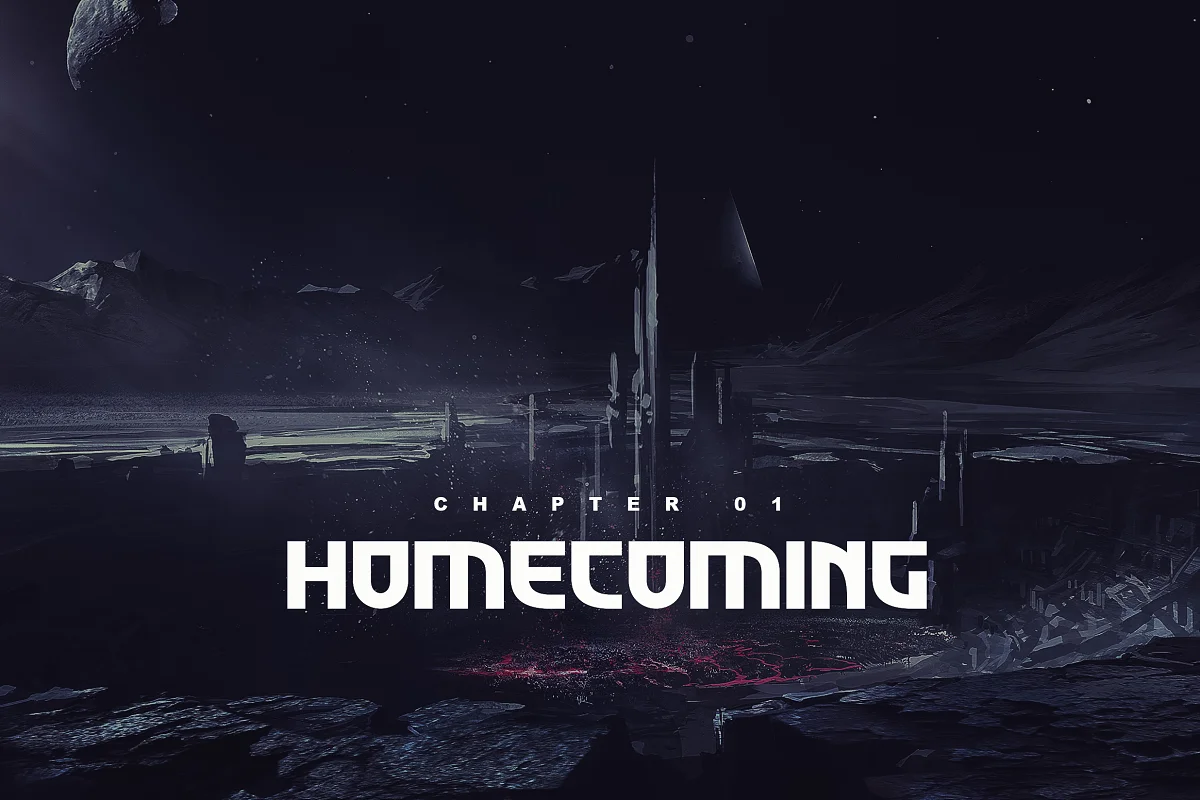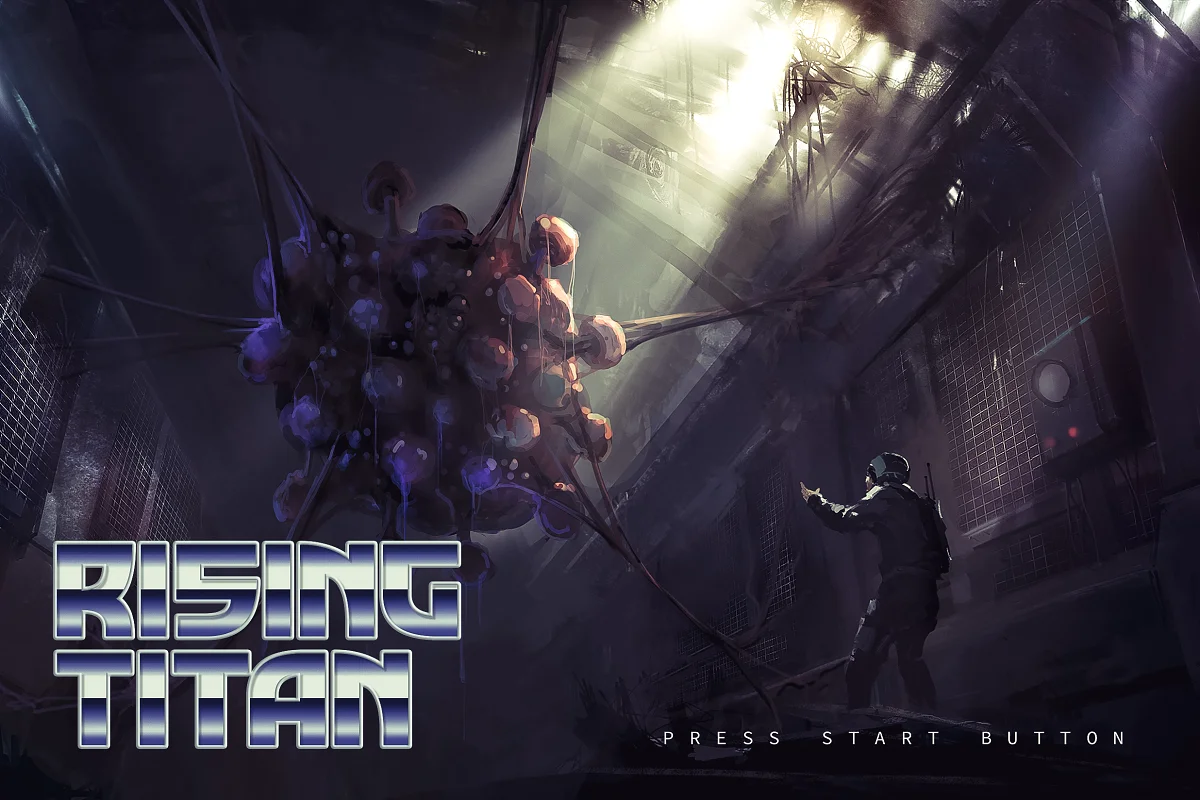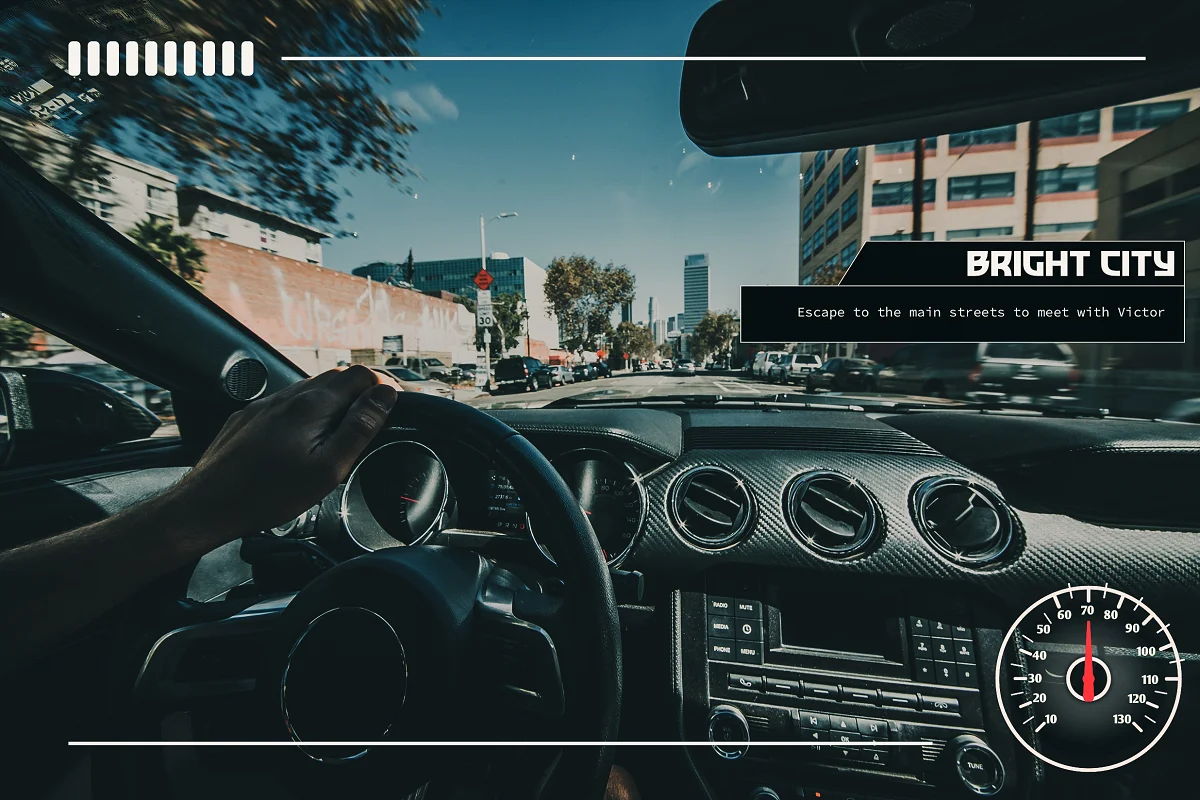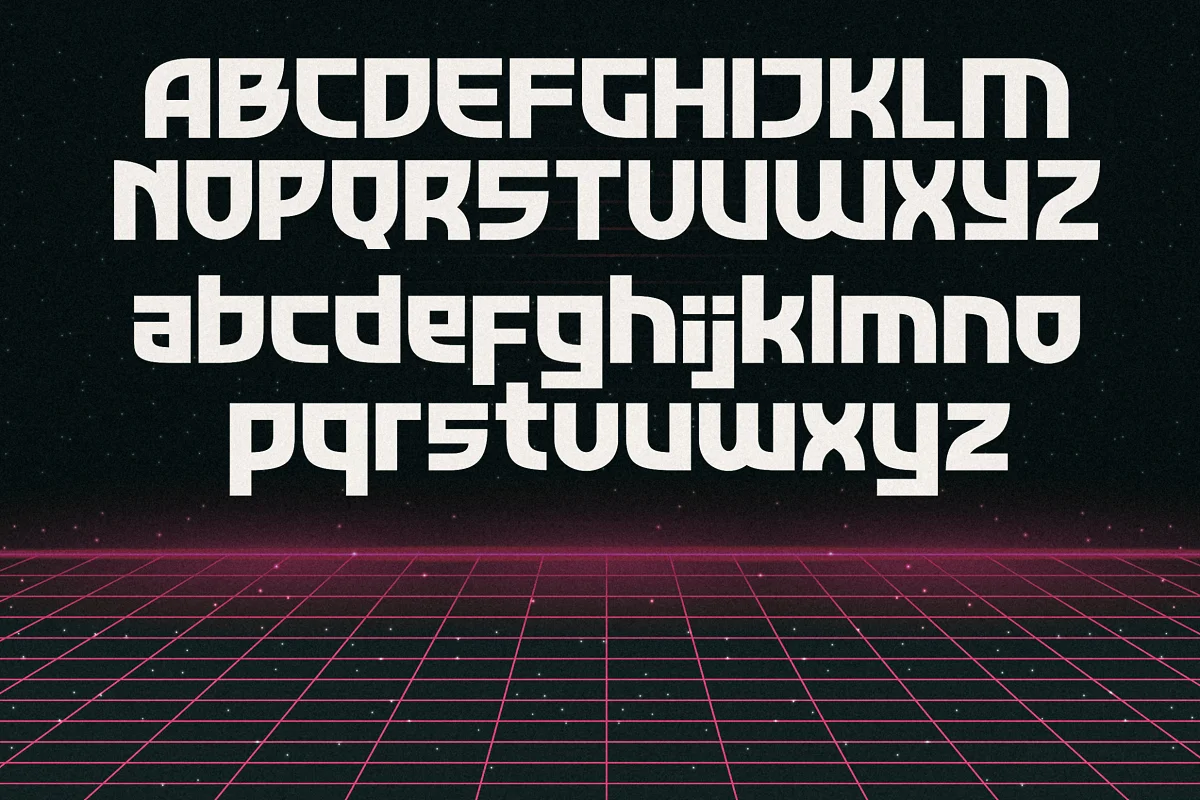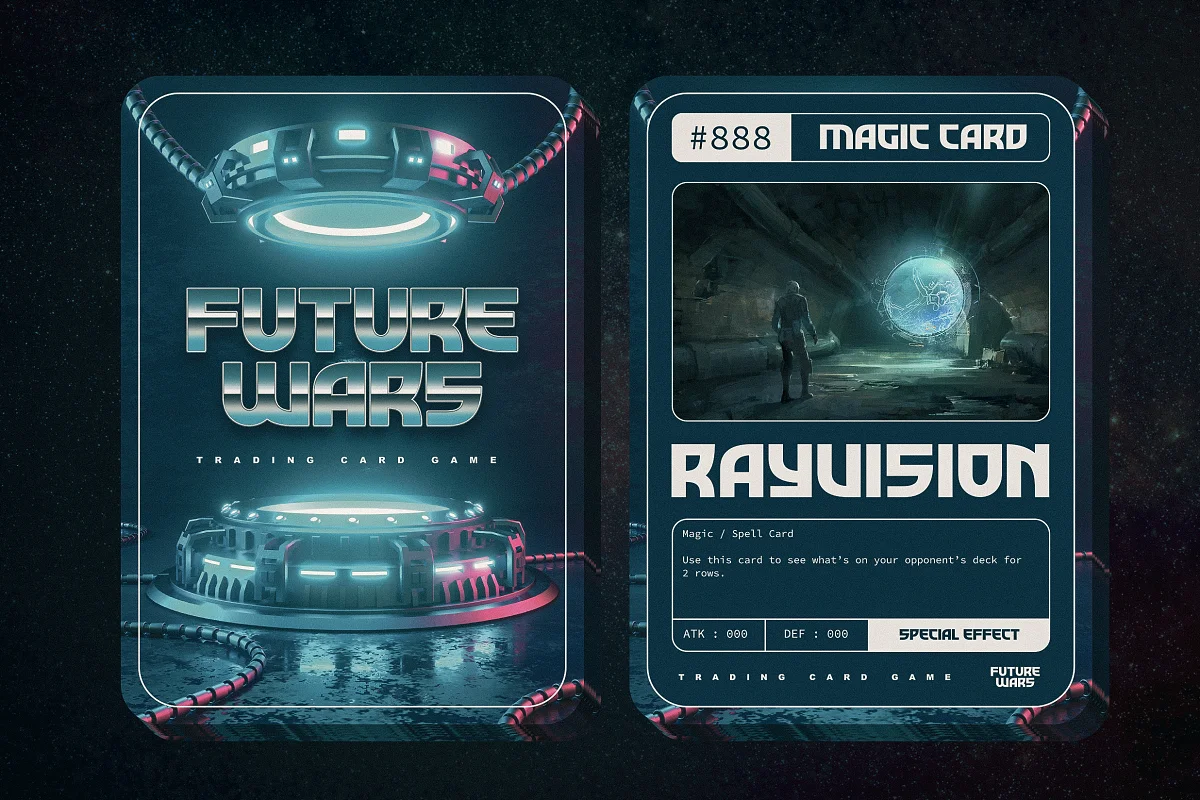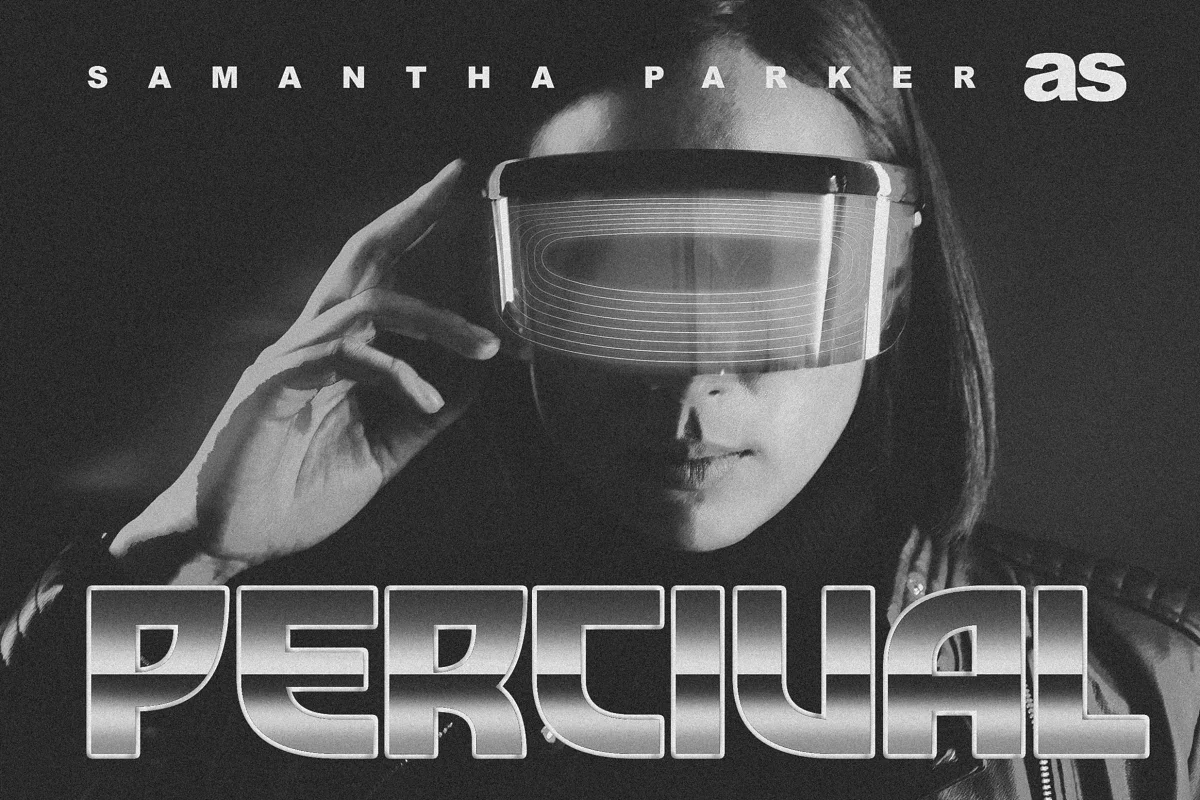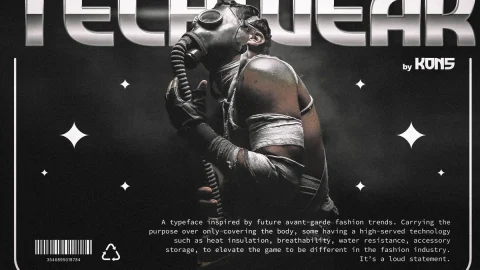
Hãy sẵn sàng bước vào kỷ nguyên tương lai hoài cổ với Techwear . Đó là một kiểu chữ tương lai lấy cảm hứng từ những năm 80 và hình ảnh về cách mọi người diễn giải lại “tương lai” trong trí tưởng tượng của họ ngày xưa.
Hoàn toàn phù hợp với khái niệm khoa học viễn tưởng, logo, thương hiệu, dự án âm nhạc, steamwave, khái niệm synthwave, poster, thiết kế trò chơi, thiết kế giao diện người dùng, bất cứ lúc nào bạn cần nhanh chóng đến kỷ nguyên tương lai cổ điển, Techwear chính là câu trả lời, các đồng chí.